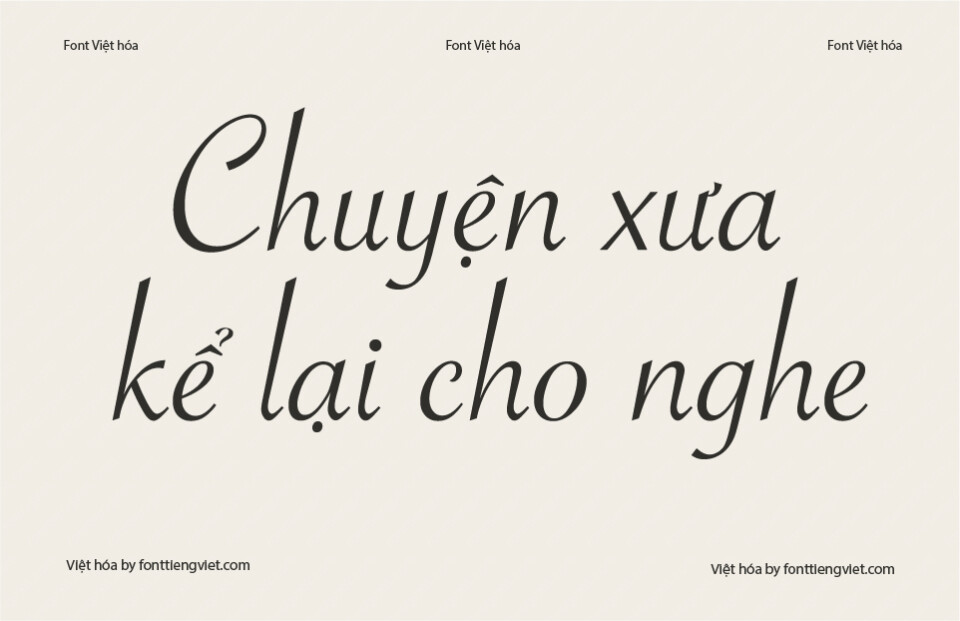
Tải Font Việt hóa 1FTV VIP Savoye – Nét Chữ Mềm Mại Cho Thiết Kế Giáo Dục
Giới thiệu về bộ Font Việt hóa 1FTV VIP Savoye
Trong thế giới thiết kế đồ họa, việc lựa chọn một Font Chữ phù hợp là yếu tố quyết định tạo nên linh hồn cho tác phẩm. Font Việt hóa 1FTV VIP Savoye nổi lên như một lựa chọn hàng đầu cho những ai yêu thích sự thanh lịch, cổ điển và đầy chất nghệ thuật. Đây là bộ font script với những đường nét uốn lượn tinh tế, mang lại cảm giác nhẹ nhàng nhưng không kém phần sang trọng. Đặc biệt, phiên bản này đã được tối ưu hóa tiếng Việt giúp người dùng sử dụng thuận tiện mà không lo lỗi hiển thị.
Tại sao học sinh và giáo viên nên sử dụng Font Việt hóa 1FTV VIP Savoye?
Với phong cách viết tay uyển chuyển, bộ font này rất phù hợp để ứng dụng trong môi trường học đường. Bạn có thể sử dụng nó để thiết kế thiệp mời họp phụ huynh, chứng nhận khen thưởng hoặc làm tiêu đề cho các bài thuyết trình sáng tạo. Sự mềm mại của các ký tự giúp nội dung trở nên gần gũi, truyền cảm hứng hơn cho người xem.
Ưu điểm nổi bật của Font Việt hóa 1FTV VIP Savoye
Khả năng tương thích và tính thẩm mỹ cao
Bộ font này được tinh chỉnh kỹ lưỡng về khoảng cách và dấu câu, đảm bảo tính thẩm mỹ tuyệt đối trên các phần mềm như Word, PowerPoint hay Photoshop. Ngoài ra, tính năng hiển thị sắc nét giúp các bản in ấn phục vụ báo tường hay trang trí lớp học trở nên chuyên nghiệp hơn bao giờ hết.
Ứng dụng đa dạng trong nhiều lĩnh vực
Không chỉ dừng lại ở giáo dục, phông chữ này còn được ưa chuộng trong thiết kế bìa sách, menu nhà hàng hay các thiệp chúc mừng ngày lễ. Sự linh hoạt trong phong cách giúp nó dễ dàng kết hợp với các font chữ không chân hiện đại để tạo ra sự cân bằng cho thị giác.